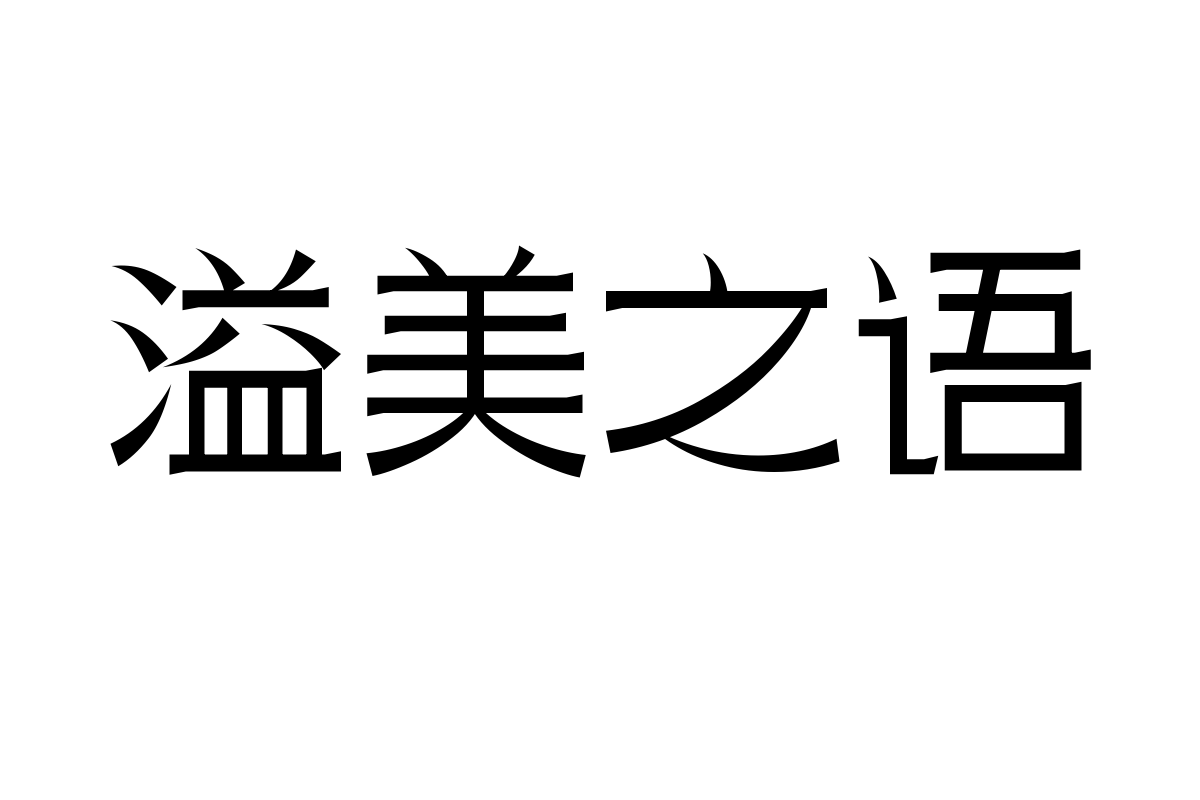
瑞丽字体(Rui Li Font)是一款具有独特风格和特色的中文简体字体。它由瑞丽设计公司开发,旨在为设计师提供一种新颖、时尚的字体选择。这款字体以其独特的线条和形状而闻名,给人一种简洁、现代的感觉。
瑞丽字体的特点包括:
1. 简洁的线条:瑞丽字体的笔画流畅且简洁,没有过多的装饰元素,给人一种干净、利落的感觉。
2. 独特的形状:瑞丽字体的形状各异,有的圆润饱满,有的尖锐锐利,这种多样性使得字体具有很强的个性和辨识度。
3. 适合多种应用场景:瑞丽字体适用于各种文字排版,无论是标题、正文还是副标题,都能很好地适应不同的设计风格和需求。
4. 易于使用:瑞丽字体支持多种字体样式和大小调整,方便设计师根据需要进行调整和使用。
总之,瑞丽字体是一款极具创意和个性的中文简体字体,适合用于各类设计项目,如广告、海报、网页等。